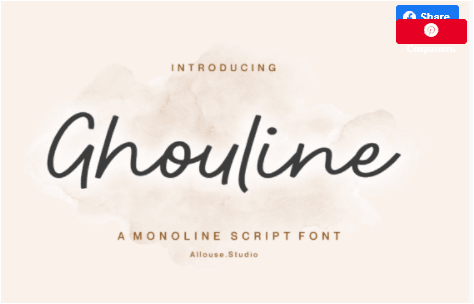
Ghouline Font
Ghouline — это деликатный рукописный шрифт. Он идеально подходит для упаковки продуктов, брендинга, обложек журналов, социальных сетей, приглашений или просто для выражения слов над фоном.